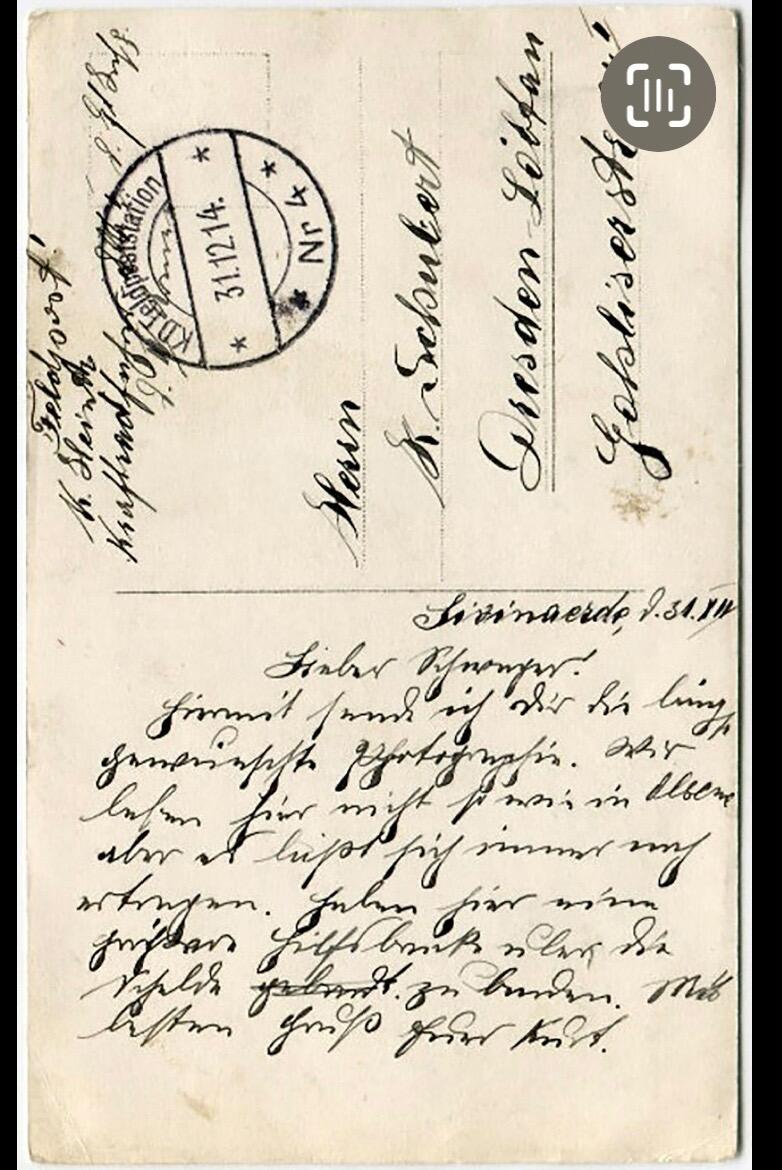
Was heißt das in Sütterlin bitte?
Ich verzweifle an dem Wort seit Tagen!!! Es muss ein Ortsname sein Deutschland/Belgien Nähe Wichelen/Schelde…..
wir haben es hier nicht so wie in ???? aber es lässt sich noch ertragen. (Alles andere habe ich entziffert)
Ich nehme an, beim Absendeort handelt es sich um Zwijnaarde bzw. in zeitgenössischer dt. Schreibweise Zwynaerde (nur mit ungewöhnlicher Zwi-Schreibung). Beim zweiten Wort habe ich auch keine Idee. Ich dachte, es handelt sich vielleicht um ein verunglücktes E am Anfang, und es läuft auf einen Vergleich mit der Heimat hinaus – die Karte geht ja in die Elbstadt Dresden. Auf den zweiten Blick aber unwahrscheinlich. Ich fürchte, ab jetzt muss man militärhistorische Recherchen anstellen (oder einen Kurrent-Geistesblitz haben). ;-)
Mit so richtig gutem Willen könnte ich Elbland [Dresden Elbland] in dem Wort lesen können. Das Wort bricht am Kartenrand ab, so dass kein Platz mehr war, um das n und d richtig auszuschreiben. Wobei es dann wohl 'im' anstelle von 'in' sein müsste.
Wären Sie bitte so nett, den ganzen Text der Postkarte aufzuschreiben? So kann ich selber weiter üben.
Albene
So weit war ich entzifferungstechnisch auch. Ich konnte nur keinen realen Ort finden, der diese Lesart plausibel gemacht hätte. Es gibt das heutige Aube in Lothringen, früher dt. Alben. Schien mir aber unwahrscheinlich. Auch weil der vierte Buchstabe als »e« ganz schön aus der Art geschlagen wäre.
Feldpost Kraftradfahrer d. K.Heintz
K.Schubert
Dresden Löbtau
Gohliserstr.24
Sisinaerde d.31.12.14
Lieber Schwager!
Hiermit send ich dir die längst gewünschte Photographie.
Wie leben hier nicht so wie in ?*(Alpen/Eupen/ ), aber es läßt sich immer noch ertragen. Habe hier eine größere Hilfsbrücke über die Schelde (gebaut) zu bauen.
Mit bestem Gruß Euer Kurt